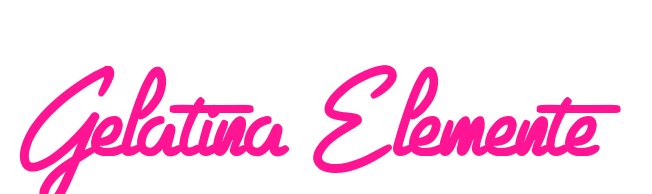
Gelatina Elemente 詳情頁(yè)
Gelatina Elemente字體字庫(kù)是一款讓人賞心悅目、百看不厭的英文字體,適合各類廣告和產(chǎn)品包裝設(shè)計(jì)應(yīng)用,字體大小0.07MB,格式為ttf字體,上傳用戶是曾紹文,作者/版權(quán)方為未知